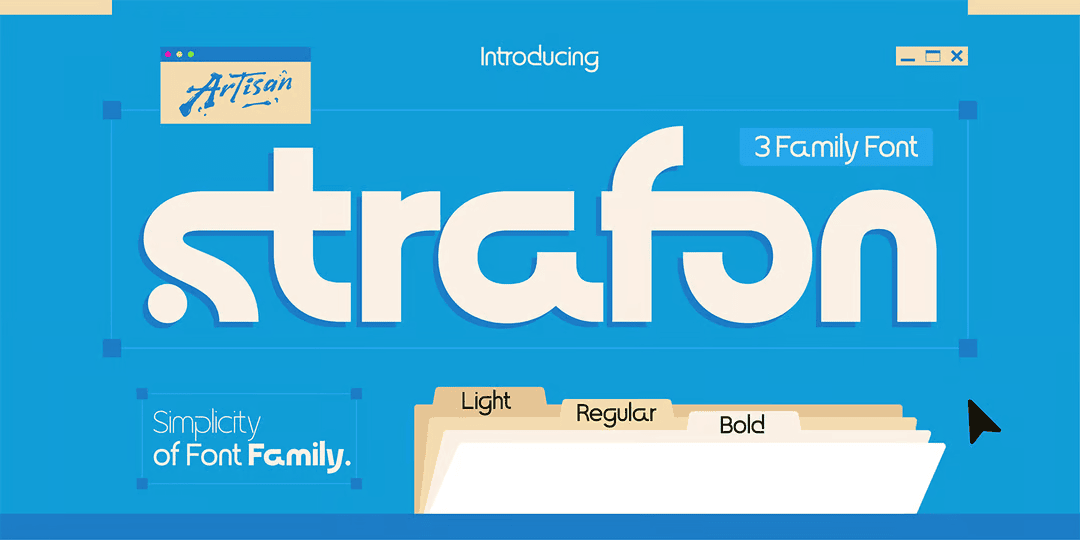
ちょっとレトロなサンセリフディスプレイ。Eurostile ぽいスクァリッシュ squarish なグロテスクで、画像のように角が丸くなった Soft と普通の Sharp の2種があり、ウェイトバリエーションがない代わりに字幅が6種類もあって、普通に組むもよし、作例のように字幅をランダムに組み合わせて組むもよしとなっている。基本的に小文字がないスモールキャップスなのだが、オルタネートに小文字型のグリフが入っており、実質小文字もあるという感じ(なんでや)。ただいま60%オフセール中。
すんごいヨレヨレのステンシルディスプレイ。まるで紙をちぎって文字を形作ったような書体で、単純なストロークは太くアウトラインはガッタガタ、あちこち切れたステンシルスタイルになっている。ただ可読性はそこまで損なわれてはおらず、意外と読める。雰囲気はチャイルディッシュなので、子供向けのあれやこれやに。ちゃんと直立している Regular と、字によってあちこちちょっとずつ傾いた Dance の2スタイル。
本日は『天使のささやきの日』。ものすごいスピ臭がするがそうではなく、天使のささやきとはいわゆる気象現象の「細氷(「ダイヤモンドダスト)」のことだそう。ダイヤモンドダストと言えば白鳥座キグナス(笑)ということでこちら。レトロSFの香りがするサンセリフディスプレイ。幅広、大きく丸くなった角、ところどころ欠けたストロークと見事にレトロSF要素が揃った書体で、今となってはあまり使い道もない(ひどい)。けどグリフはスッキリしているので、アケ組みすれば少しは今っぽくなると思う。アウトラインがジャギジャギした Rusty スタイルと2種あって、それぞれ3ウェイトずつ。
コリッとしたグリフが特徴的なジオメトリックサンセリフディスプレイ。北欧のルーン文字のような直線的なストロークのスタイルを取り入れた書体で、円部分はほぼ真円なので、そのコントラストがおもしろい。ストロークの端はほんのり斜めにカットされ、接続部分はところどころ角がちょんと付いた程度になっていたりする。9ウェイトもあるのでディスプレイやロゴなどに幅広く使えるだろう。名前は韓国語ではなくフィンランド語で “luck” のような意味らしい。カムサハムニダ~。
個性的なグリフを持つジオメトリックサンセリフディスプレイ。見ての通りちょっと変わったファンシーな書体で、画像はストロークの端が丸くなったいわゆる丸ゴシックだが、普通にスパッと裁ち落とされたバージョンと2種類がある。グリフはデフォルトでは個性的な感じだが、何の変哲もないマトモなバージョンもオルタネートにある。けどそれを使うなら普通のサンセリフで良くね?となるので、多分あまり出番はないだろう(笑)。サンセリフとラウンドサンズ双方とも3ウェイトずつ。
今年も2月4日という名のファウンダリーの書体を紹介。トラック型長楕円をベースにしたジオメトリックサンセリフディスプレイ。まあよくあるような DIN タイプのサンセリフだが、小文字がユニケースで大文字と同じサイズになっており、b や g などアセンダーやディセンダーが必要なグリフはなく、大文字と同じ形となっている。画像のようにランダムに組み合わせると個性が出るだろう。ウクライナ産らしくキリル文字もサポートしている。オブリークタイプのイタリックもあって6ウェイト。
ちょっと変わったグリフが特徴的なレタリングスクリプト。見ての通りなかなか大文字のクセの強い書体で、初見で S や L を見分けるのは結構難しい(笑)。小文字は基本的に普通のプロポーションではあるが、アセンダーやディセンダーが極端に長いので、結果的にコンデンスっぽくなっている。大文字にはグリフ違い、小文字には水平なエンディングストロークが付いたオルタネートがある。他リガチャーもちょこちょこあり。この辺はレトロアメリカンな雰囲気で統一されてしまうのが常だが、こちらはやや風変わりで面白いと思う。1ウェイト。
ポップで個性的なジオメトリックサンセリフディスプレイ。基本はカクカクしたシャープなアウトラインをしているが、ストロークが繋がる箇所で丸くカーブが取られており、その両極端なコントラストがおもしろいシルエットを生み出している。やや幅広で短いアセンダーやディセンダーのずんぐりしたプロポーションがポップでかわいらしい。ゲームやスタートアップのロゴなどに似合うと思う。9ウェイト。
本日はモーツァルト Wolfgang Amadeus Mozart の誕生日(1756)なのでこちら。ややアール・ヌーヴォー風味のあるサンセリフディスプレイ。コンデンスなプロポーションに、手書きのようなやや不安定なグリフとストロークの書体で、見ての通りスワッシュオルタネートがある。ウェイトに Regular と Bold がある他、フィルに線が入った Inline と荒れた Grange があり、この4つの要素がそれぞれ絡み合って13種のバリエーションがある。大文字のみ。
スクァリッシュ(squarish = 四角い)でレトロ感のあるサンセリフディスプレイ。Eurostile のような四角いプロポーションをベースにしたサンセリフで、このスタイルは ’60~’70年代に流行ったので自然とレトロ感が生まれている。g が個性的なグリフをしているが、他はさほど奇抜さはなく、素直な書体である。ファミリー展開が豊富で、字幅が4種類あり、それぞれにイタリックもあって9ウェイトで合計72種。その他にバリアブルタイプもあり。現在 MyFonts のベストセラー50位らしい。